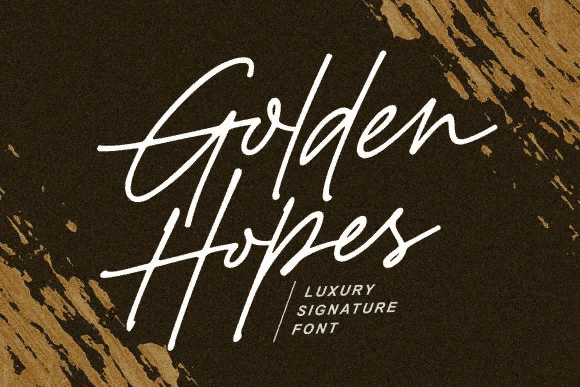
Название: Golden Hopes Font (2021)
Golden Hopes - ослепительный шрифт.
Этот шрифт аккуратно выполнен и отличается высокой детализацией. Независимо от темы, этот шрифт станет прекрасным дополнением к вашей библиотеке шрифтов, поскольку он способен улучшить любое творение.